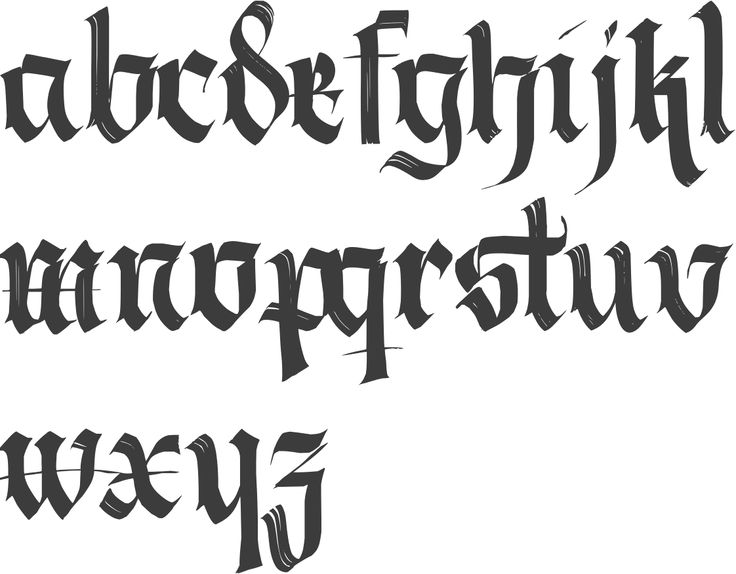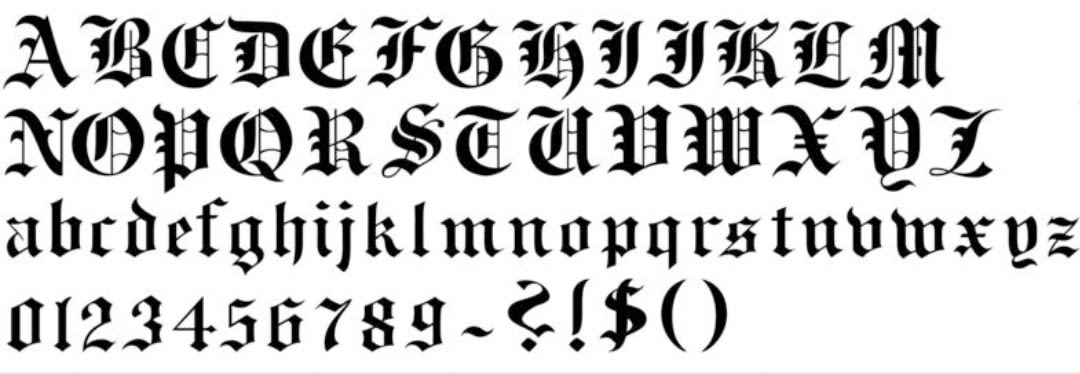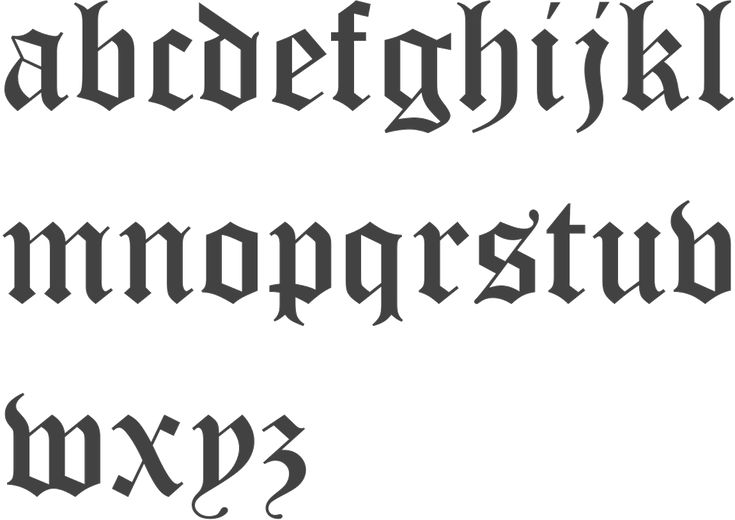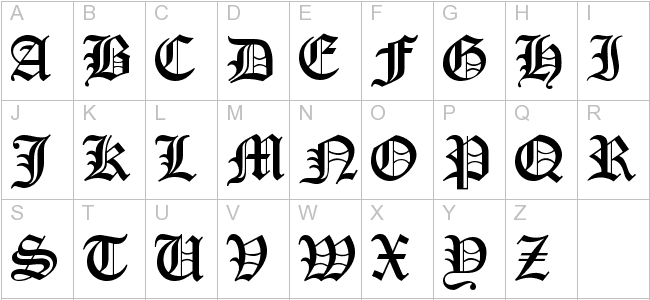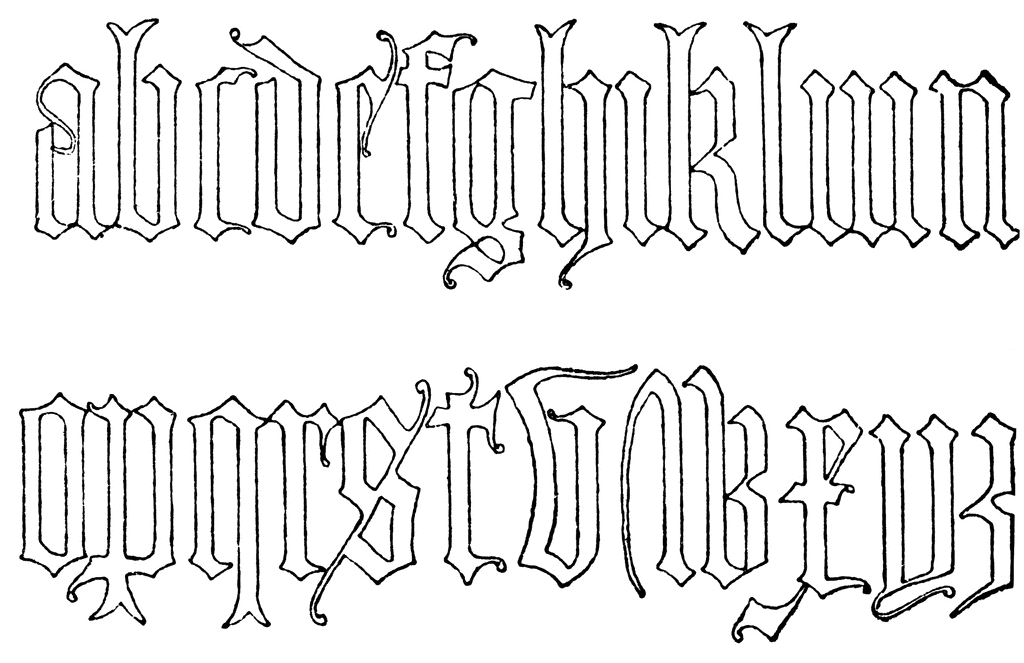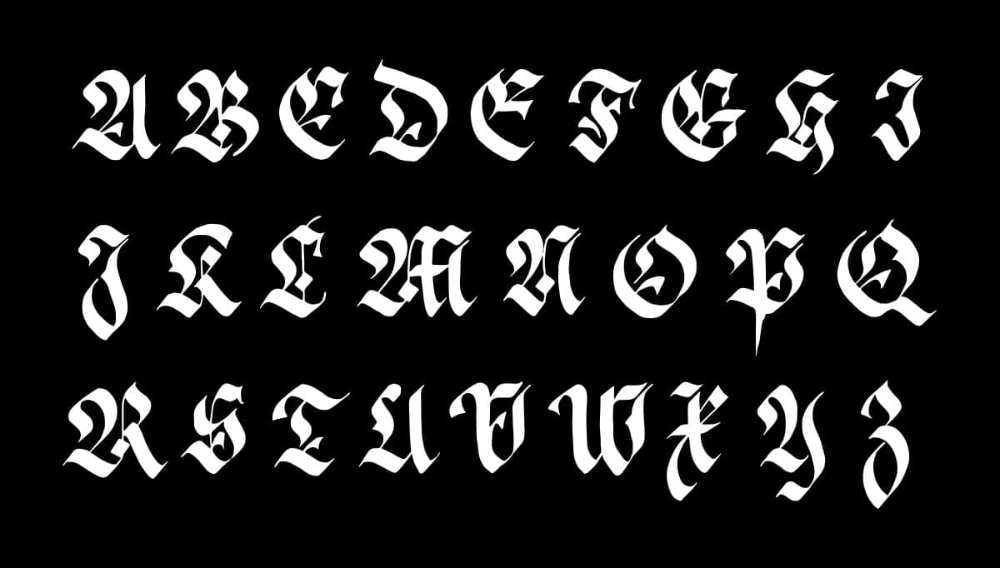
Психология восприятия шрифтов
Будучи частью фирменного стиля, шрифт ассоциируется с продукцией бренда и является одним из важнейших средств коммуникации компании с потребителями.
Согласно последним исследованиям психологов, правильно подобранный шрифт задает человеку настроение во время чтения текста. В действительности, одно и то же слово, набранное разными шрифтами, будет совершенно по-разному восприниматься. К тому же, необходимо помнить о целевой аудитории, для которой создается рекламное сообщение.
Например, деловые партнеры вряд ли оценят легкий игривый шрифт, а дети не будут в восторге от строгой прямой надписи.
Влияние шрифта на эмоциональное восприятие потребителем бренда
Психологи выделяют несколько следующих типов шрифтов по их влиянию на настроение потребителей.
Прямые вытянутые шрифты
Сообщают деловое настроение и являются практически универсальными шрифтами. Тем не менее, следует учитывать, что прямой шрифт будет неуместен для немассовой и оригинальной продукции, которую необходимо выделить среди конкурентов. Здесь он может показаться скучным и безликим, если не обыграть его необычным цветовым решением.
Строгие квадратные шрифты
Преимущественно используются в дизайне рекламы промышленных продуктов, технологий и социальной рекламы. Здесь неуместна легкость и простота, эти шрифты призваны настроить человека на серьезность предоставленной информации. Они создают впечатление важности и авторитетности, поэтому рассчитаны на привлечение партнеров по бизнесу и инвесторов.
Округлые шрифты
Передают чувство комфорта и уюта. В то время как квадратные шрифты выглядят суровыми, округлые положительно воспринимаются как доброе отношение бренда к потребителям.
Наклонные шрифты с виньетками
Чаще всего используются для рекламы товаров, у которых целевая аудитория девушки и женщины.
Наклонные шрифты вызывают чувство легкости и красоты. Так рекламируют салоны красоты, магазины одежды и косметики. Курсив облегчает восприятие информации, и она выглядит менее важной. Поэтому курсивом выделяют примечания и авторские отступления.
Рукописные шрифты
Не подходят для наружной рекламы так же, как и наклонные шрифты – их сложно читать, если выбран большой размер букв. В то же время, они отлично подходят для того, чтобы подчеркнуть эксклюзивность товара или услуги. Рукописные шрифты используют при рекламе адвокатских и консалтинговых услуг, врачебной практики, для написания пригласительных, при проведении политических пиар-акций. Они вызывают чувство доверия и придают большую достоверность информации.
Стилизованные декоративные шрифты
Шрифты, выглядящие как граффити или готические надписи, стоит использовать только там, где они будут нести соответствующую смысловую нагрузку. Например, совершенно неуместно использовать готический шрифт для рекламы парикмахерской или детского магазина.
В то же время, он будет хорошо смотреться на вывеске тематического бара.
Самые популярные шрифты
1. С засечками: Baskerville, Didot, Garamond, Georgia, Times. Ассоциации: традиционный, утонченный, практичный, формальный.
2. Без засечек: Avenir, Futura, Gill Sans, Helvetica, Verdana. Ассоциации: современный, чистый, геометрический, универсальный.
3. Рукописные: Buttermilk, Edwardian, Isabella, Snell Roundhand, Zapfino. Ассоциации: элегантный, классический, утонченный, стильный.
4. Брусковые: Clarendon, Copse, Josefin, Museo, Silverfake. Ассоциации: современный, модный, дружественный, цельный.
Отличие восприятия шрифта с засечками и без них
Шрифты с засечками (serif) читаются легче в печатных работах. Засечки увеличивают контраст между буквами и делают их отличительными. Так нашему мозгу легче распознать букву. Читая шрифт без засечек, мозг тратит больше времени на то, чтобы опознать букву, потому что ее форма не такая отличительная.
Шрифты без засечек (sans serif) лучше использовать для интернета.
Также sans serif шрифт хорошо смотрится в наружной рекламе, так как не теряет своих свойств при увеличении. Его часто используют для того, чтобы привлечь внимание. Шрифт без засечек хорошо смотрится и в маленьком размере, но для основного текста лучше использовать с засечками – он не вызывает быстрой усталости.
40% заголовков интернет-изданий написаны с использованием шрифтов с засечками. 66% сайтов используют шрифт без засечек для основного текста.
Существует мнение, что примером удачно выбранного шрифта является такой шрифт, на который читатель не обращает внимания.
Восприятие шрифта в составе логотипа
Всего 6% интернациональных брендов используют в качестве логотипа картинку. 56% используют комбинацию текста и изображения, а логотипы оставшихся 37% брендов – это надписи. Таким образом, подавляющее большинство компаний используют текст при создании логотипа. Нельзя пренебрегать значением шрифта и необходимо уделять достаточно времени созданию логотипа с таким шрифтом, который будет лучше всего сообщать человеку философию бренда.